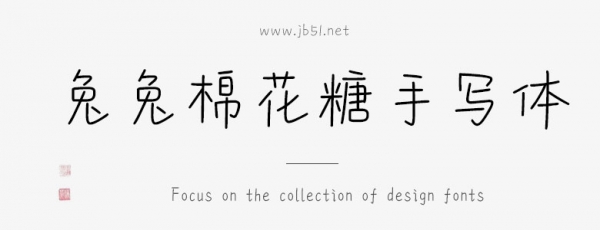
兔兔棉花糖手寫體 Bold/Regular由元寶團(tuán)子出品的藝術(shù)字體,字體筆觸略細(xì),書寫流暢,適合應(yīng)用于藝術(shù)設(shè)計(jì)、平面宣傳設(shè)計(jì)、網(wǎng)頁(yè)設(shè)計(jì),書法字帖等領(lǐng)域。有需要的朋友快來(lái)本站下載使用吧。